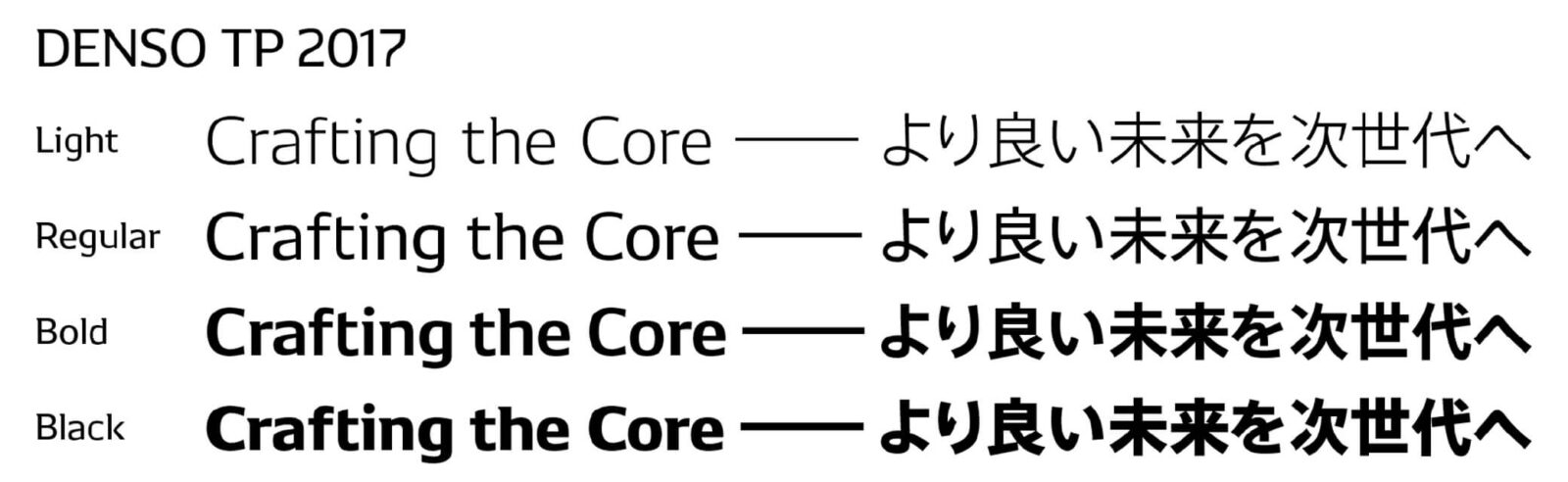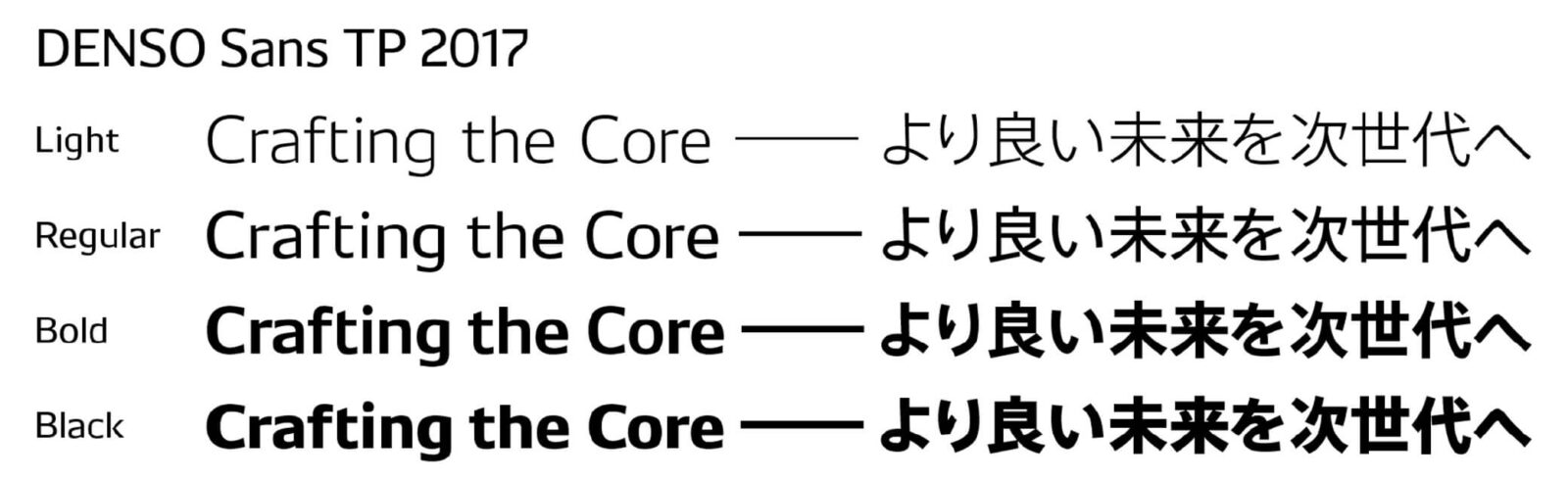
タイププロジェクト、デンソーのコーポレートフォントとして「DENSO TP 2017」「DENSO Sans TP 2017」を提供
タイププロジェクト株式会社(東京都練馬区 代表取締役社長 鈴木 功、以下、タイププロジェクト)は、株式会社デンソー(愛知県刈谷市昭和町 1-1 以下、デンソー)がタイププロジェクトの AXIS Font のカスタマイズ版をコーポレートフォントとして導入したことを発表しました。デンソーのコーポレートフォントとなる「DENSO TP 2017」と「DENSO Sans TP 2017」は、欧文書体と数字をデンマークコペンハーゲンに本拠地を置く、Kontrapunkt(以下、コントラプンクト)が制作しました。
デンソーは、ブランディング強化の施策として、コーポレートフォントを新しく導入しました。タイププロジェクトは、自社のフィットフォント技術により、コントラプンクトが開発した欧文フォントに合わせて AXIS Font のウエイトを調整し、欧文書体の和文書体への組替えエンジニアリングを行いました。
デンソーのアートディレクター 村松正巳氏は、次のように述べています。「デンソーを表現する重要な要素のひとつが、デンソーオリジナルの欧文書体です。『革新的な技術で、より良い未来を次世代に届けていく』という思いを表現するために、細部にまでこだわりました。この欧文書体に合う書体として AXIS Fontを選択しました。フィットフォントによる組替えサービスにより、最適な状態にすることができました」
「DENSO TP 2017」と「DENSO Sans TP 2017」は、デンソーの広告やウェブサイト、カタログなどで広く使用されています。
コントラプンクトの創設者であり、欧文書体をデザインしたエグゼクティブデザインディレクターの BoLinnemann(ボー・リンネマン)氏は、「デンソーを表現するためのオリジナルフォントを制作できたことはとても光栄です。セリフ体とサンセリフ体の両方に AXIS Font を組み合わせたことで、コーポレートフォントとしての活躍の場が広がると確信しています」と述べています。
タイププロジェクトの鈴木功は、「フィットフォントを基盤としたカスタマイズフォントをデンソーのコーポレートフォントとして提供することができ嬉しく思っています。今後も、コントラプンクトのような海外のフォントメーカーと協業することで、フィットフォントの可能性が広がることを楽しみにしています」と述べています。